ゴシック体×欧文フォントのおすすめ合成フォント12選|見出し・本文をおしゃれに仕上げる組み合わせ
和文のゴシック体と欧文フォントを組み合わせる「合成フォント」は、見出しや本文の印象を大きく変えるデザイン手法です。
組み合わせ次第で、スタイリッシュにも親しみやすくも仕上げられるため、紙・Webを問わず幅広く活用できます。
今回は、デザイン制作歴19年の視点から、使いやすく洗練されたおすすめのゴシック体×欧文フォントの組み合わせをご紹介します。
1. ゴシックMB101 + Helvetica
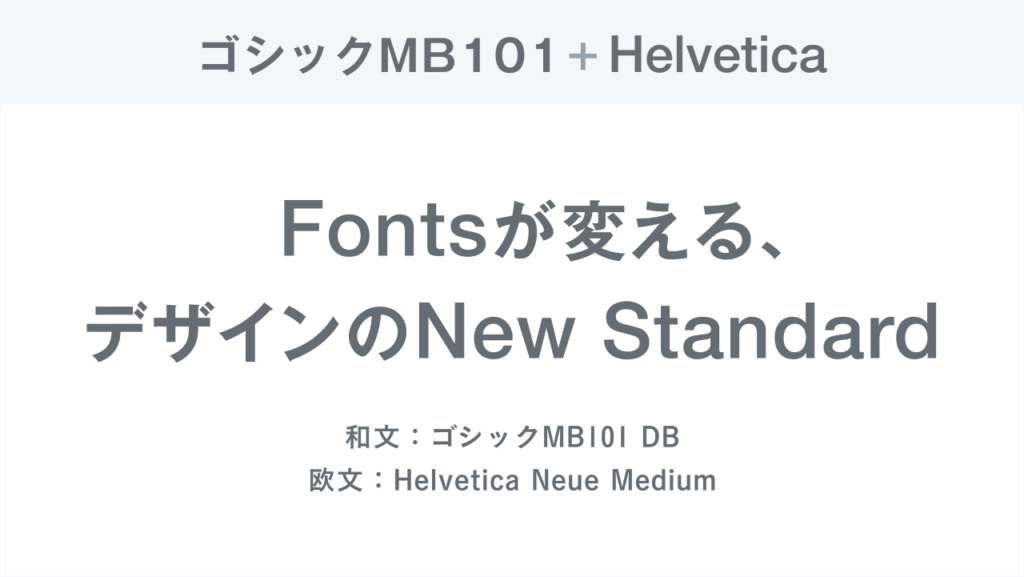
力強さと安定感を兼ね備えた組み合わせ。落ち着いた印象が求められる場面に最適です。
2. 見出しゴ + DIN
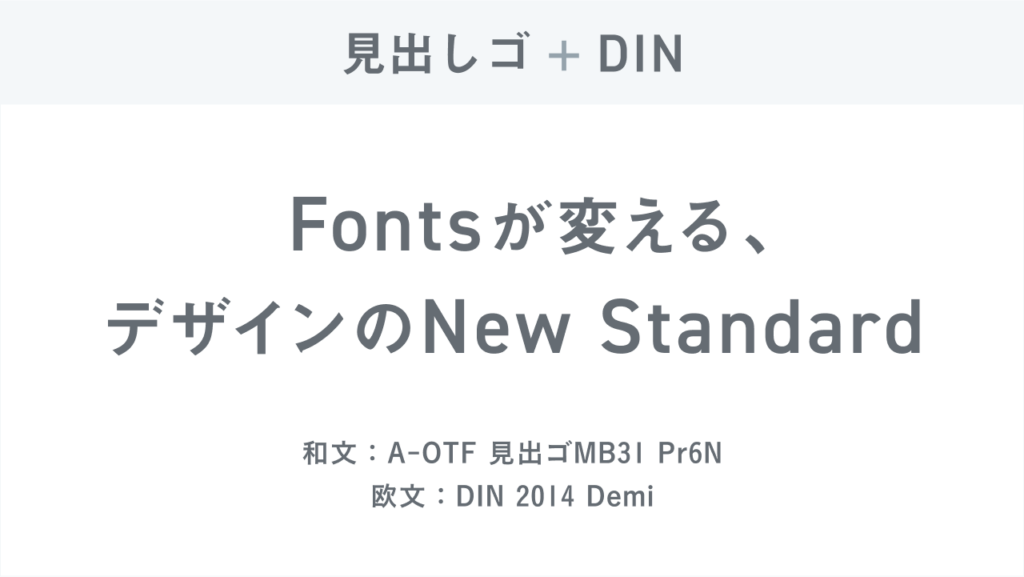
直線的でモダンな印象を持つペア。テクノロジー、建築、工業系など、硬質な雰囲気を出したいときにおすすめです。
3. こぶりなゴシック + DIN
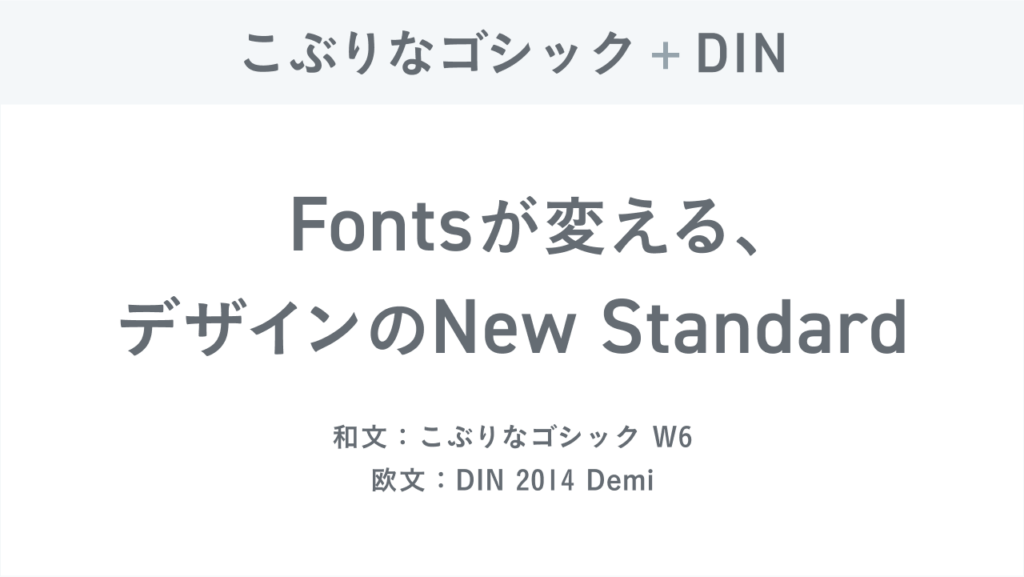
可読性とスタイリッシュさのバランスが良く、雑誌やWebメディアの見出しにぴったりです。
4. こぶりなゴシック + Futura
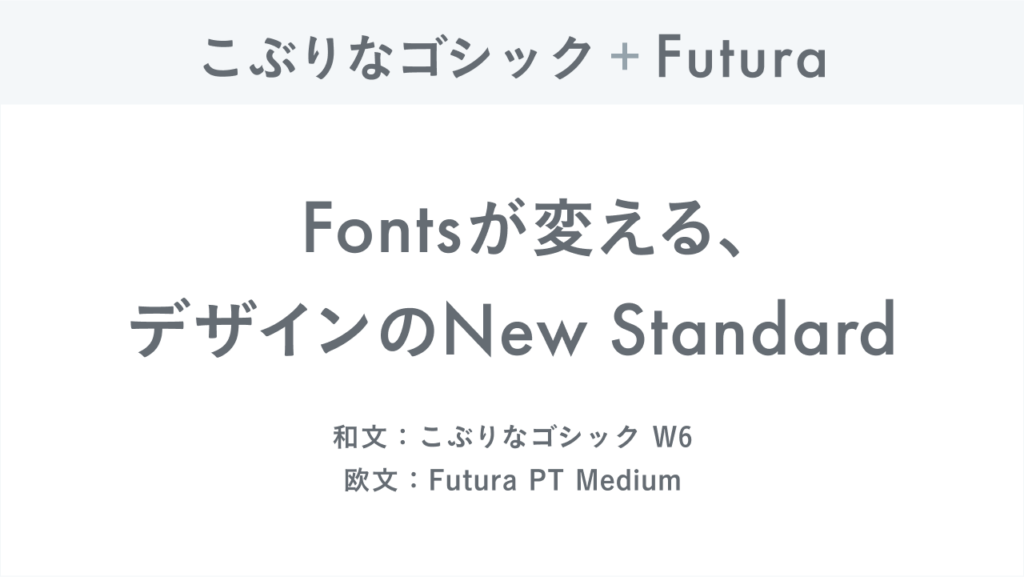
柔らかさを持ちながら、すっきりとした現代的な印象を演出できます。女性向けデザインやライフスタイル系にもマッチします。
5. UD新ゴ + Futura
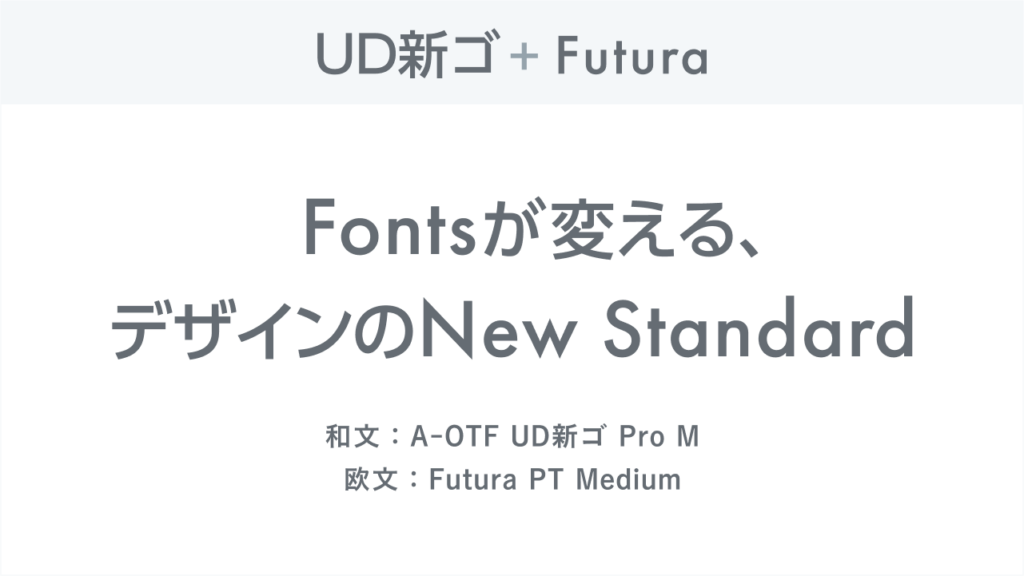
視認性が高く、洗練された雰囲気を出せる組み合わせ。公共施設や教育関連のデザインにも使いやすいです。
6. UD新ゴ + コーポレート・ロゴ + DIN
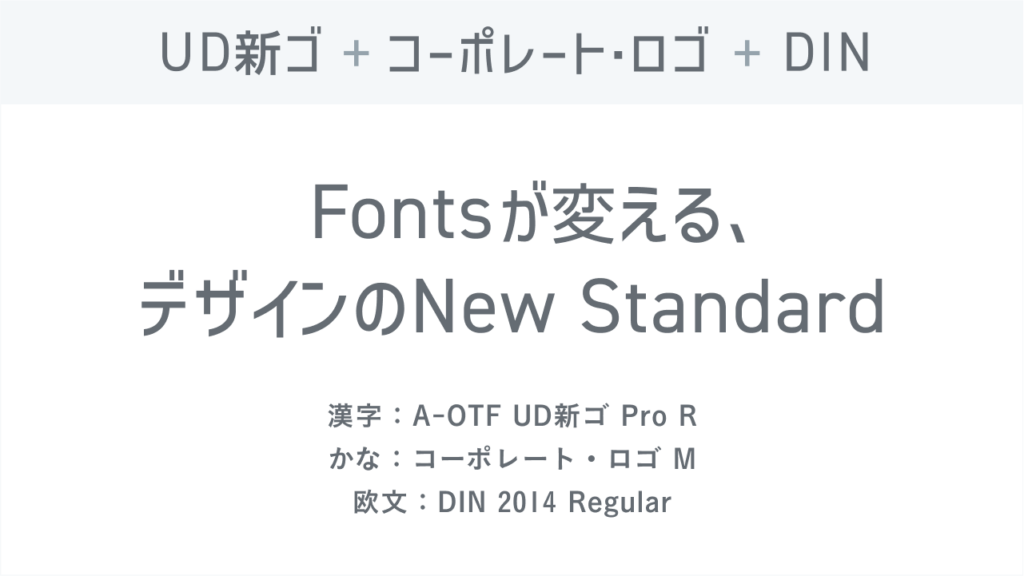
ブランド感と信頼感を同時に高められる三段構えの組み合わせ。
7. 太ゴ × Futura
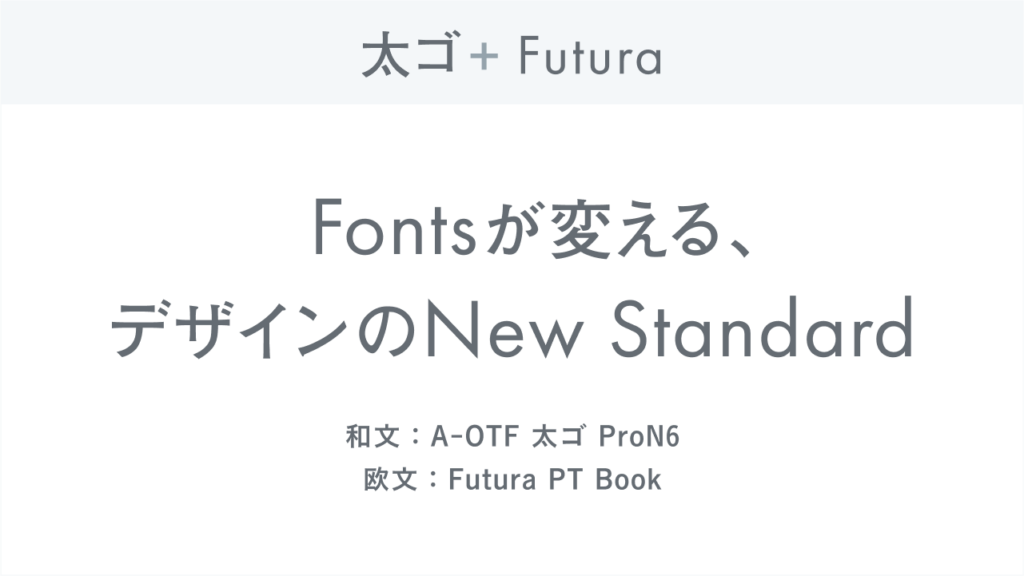
繊細かつ存在感のあるタイトルを作れるペア。本文の文字組に向いています。
8. 筑紫ゴシック + Futura
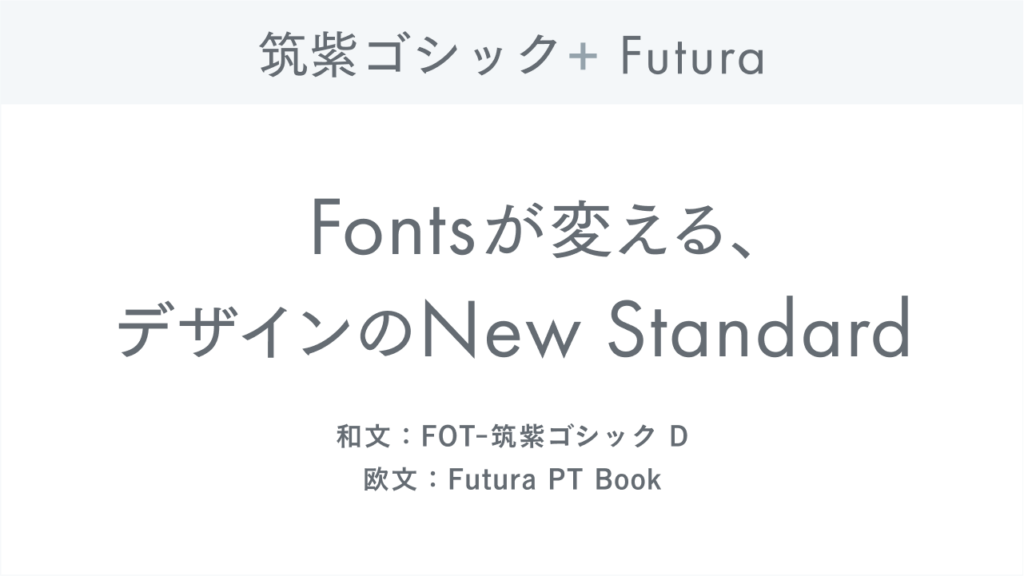
やわらかな印象と現代感を両立。ナチュラルな雰囲気を作りたい方におすすめです。
9. ヒラギノ角ゴ + DIN
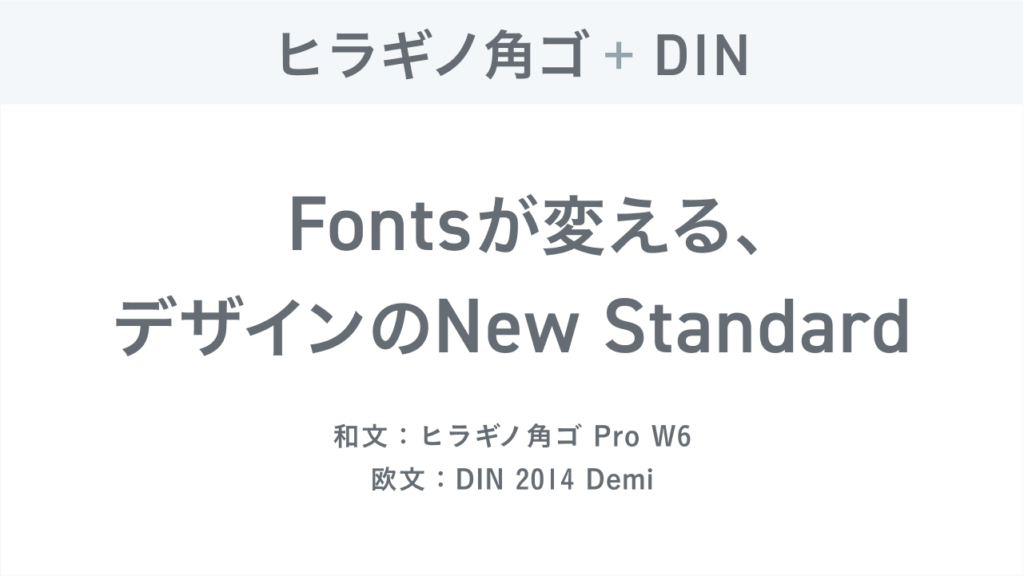
洗練されつつもクセのない組み合わせ。Webサイトから印刷物まで幅広く使えます。
10. Noto Sans + Helvetica
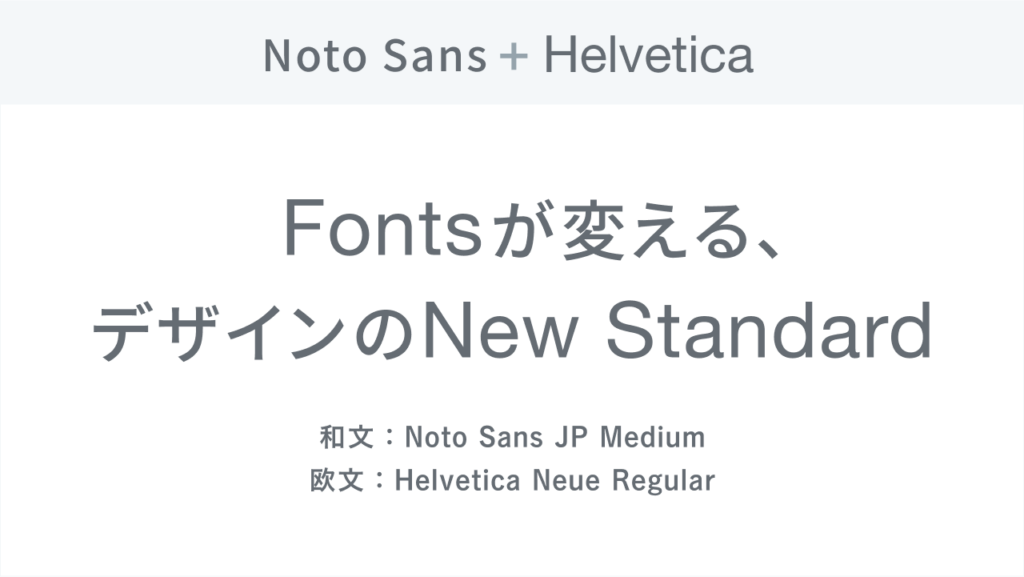
汎用性の高い組み合わせで、異なるプラットフォームでも違和感なく展開できます。
11. 游ゴシック + Helvetica
落ち着きと高級感を兼ね備え、シンプルな構成でも上品に仕上がります。
12. 游ゴシック + Avenir
モダンで柔らかい雰囲気を出したいときにぴったり。ファッションや美容関連のデザインにも向いています。
まとめ
合成フォントは、和文と欧文それぞれの特徴を活かすことで、デザインの完成度をぐっと高められます。
今回ご紹介した組み合わせは、私が実際に使って効果的だったものばかり。ぜひ、自分の制作物に合わせて試してみてください。